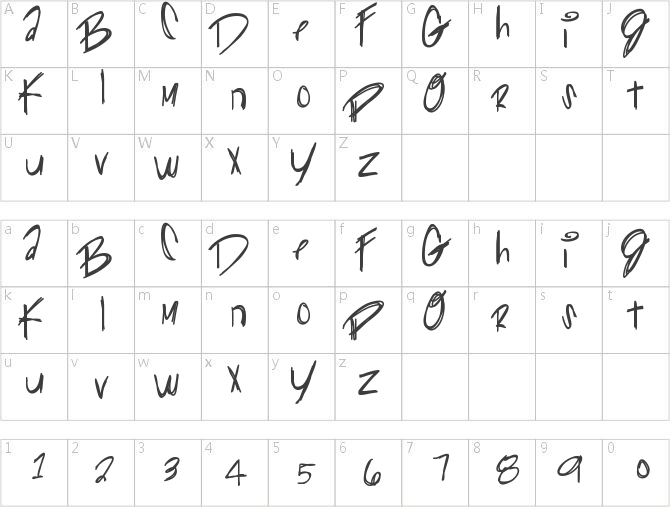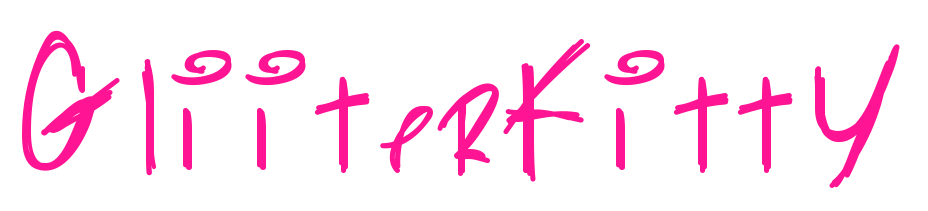
GliiterKitty 詳情頁
字體名稱: Gliiter
GliiterKitty
GliiterKitty介紹
GliiterKitty字體字庫是一款讓人賞心悅目、百看不厭的英文字體,適合各類廣告和產品包裝設計應用,字體大小0.03MB,格式為ttf字體,上傳用戶是shiqiuping,作者/版權方為未知